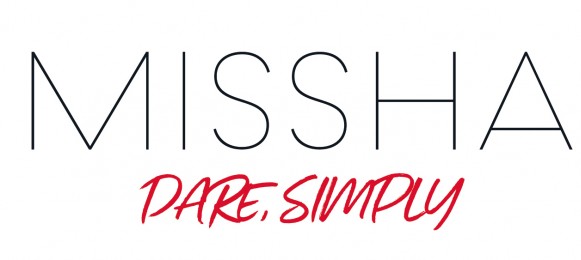
미샤, 12년 만에 새 BI와 슬로건 발표…”재도약의 원년”
<미샤의 새 BI와 슬로건>
미샤가 새 BI를 발표했다.
에이블씨엔씨는 화장품 브랜드 미샤가 12년 만에 새로운 BI를 선보였다고 지난 18일 밝혔다.
미샤의 새 BI는 거추장스러움을 배제하고 단순하고 과감하게 아름다움에만 집중하겠다는 의미를 담았다. 화려한 외형뿐만 아니라 내면의 아름다움과 자신의 가치를 소중하게 생각하는 현대 여성의 라이프스타일을 반영하겠다는 설명이다.
새로운 브랜드 슬로건 ‘DARE, SIMPLY(심플함을 위한 대담함)’는 군더더기를 걷어내고 본질을 향하겠다는 각오를 나타냈다. ‘자기다움’을 소중하게 생각하는 미샤 고객들을 응원하는 메시지이기도 하다.
<미샤의 새 엠블럼>
함께 공개한 엠블럼도 미(美)를 추구하는 모습을 표현했다. 엠블럼 속 ‘Mi’는 미샤의 ‘미’와 아름다움의 ‘미’를 상징한다. Mi를 감싼 원은 아름다움을 지키는 품질에 대한 회사의 약속을 의미한다.